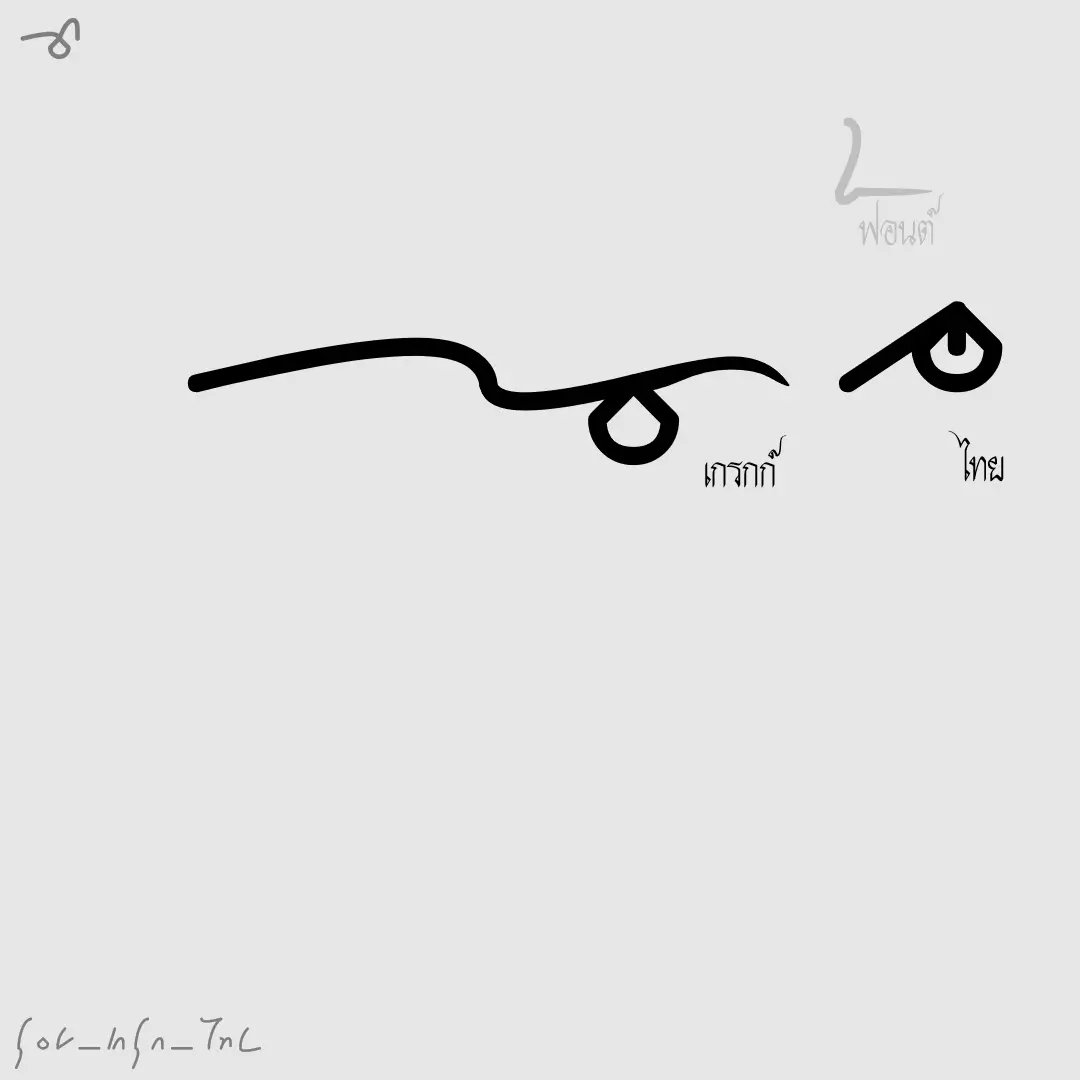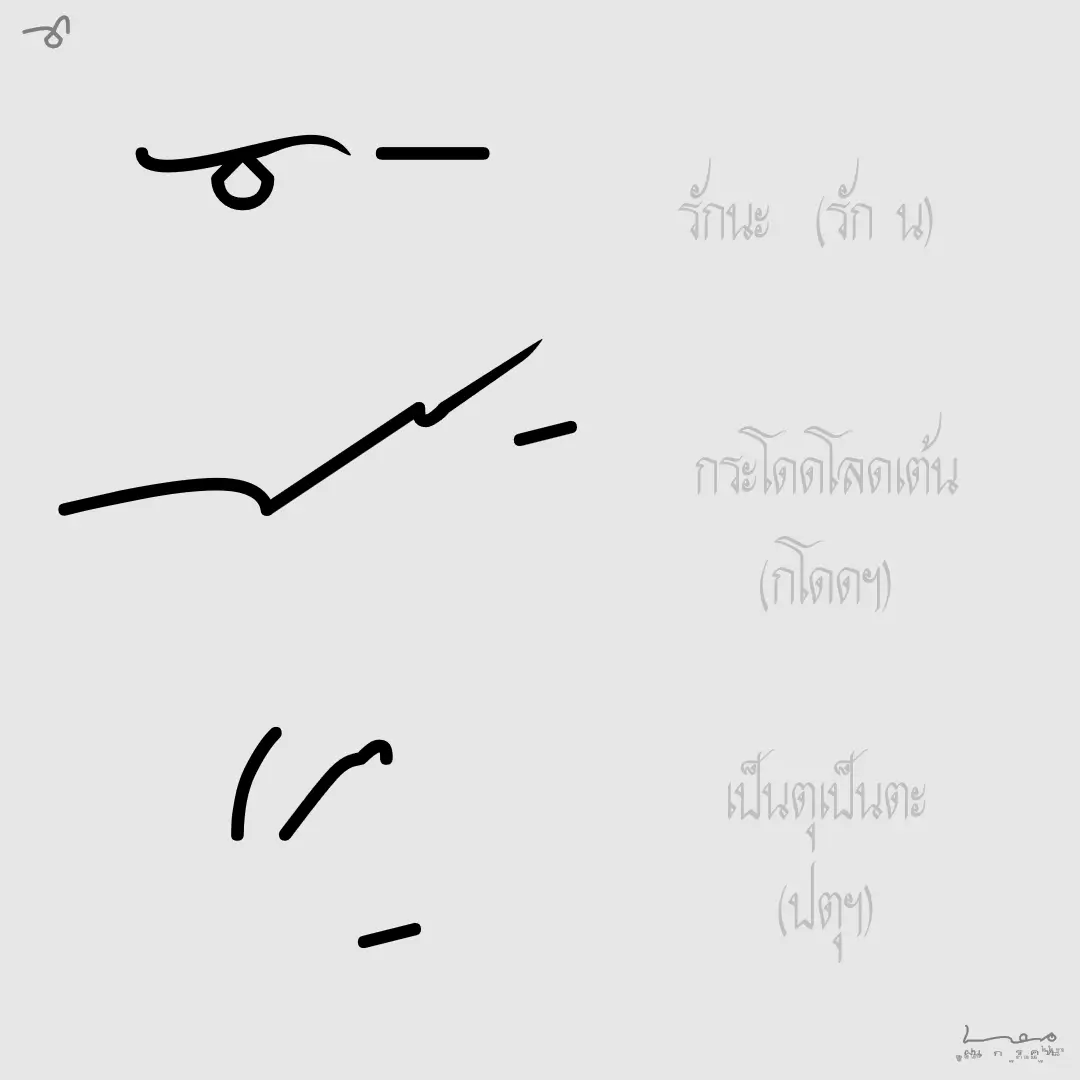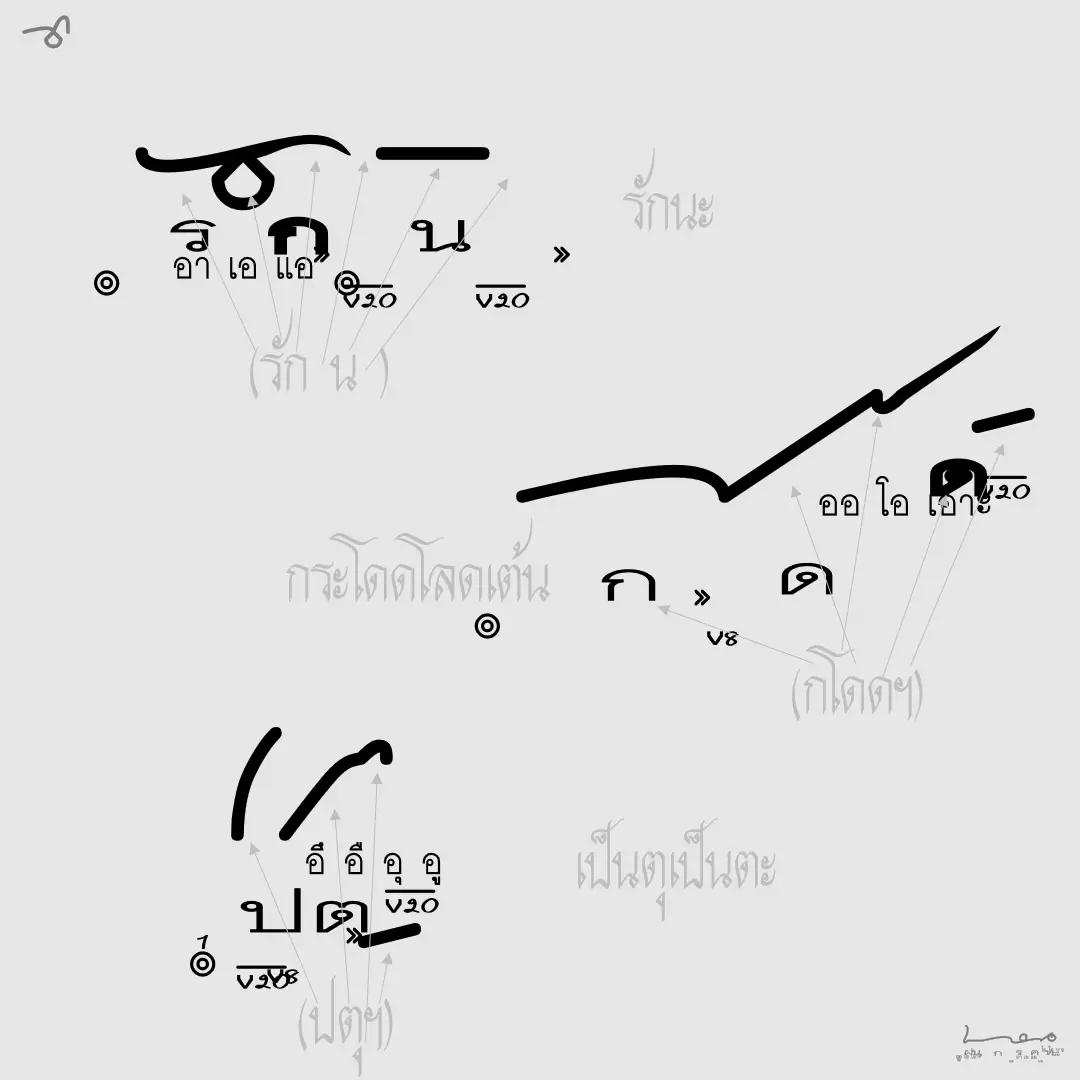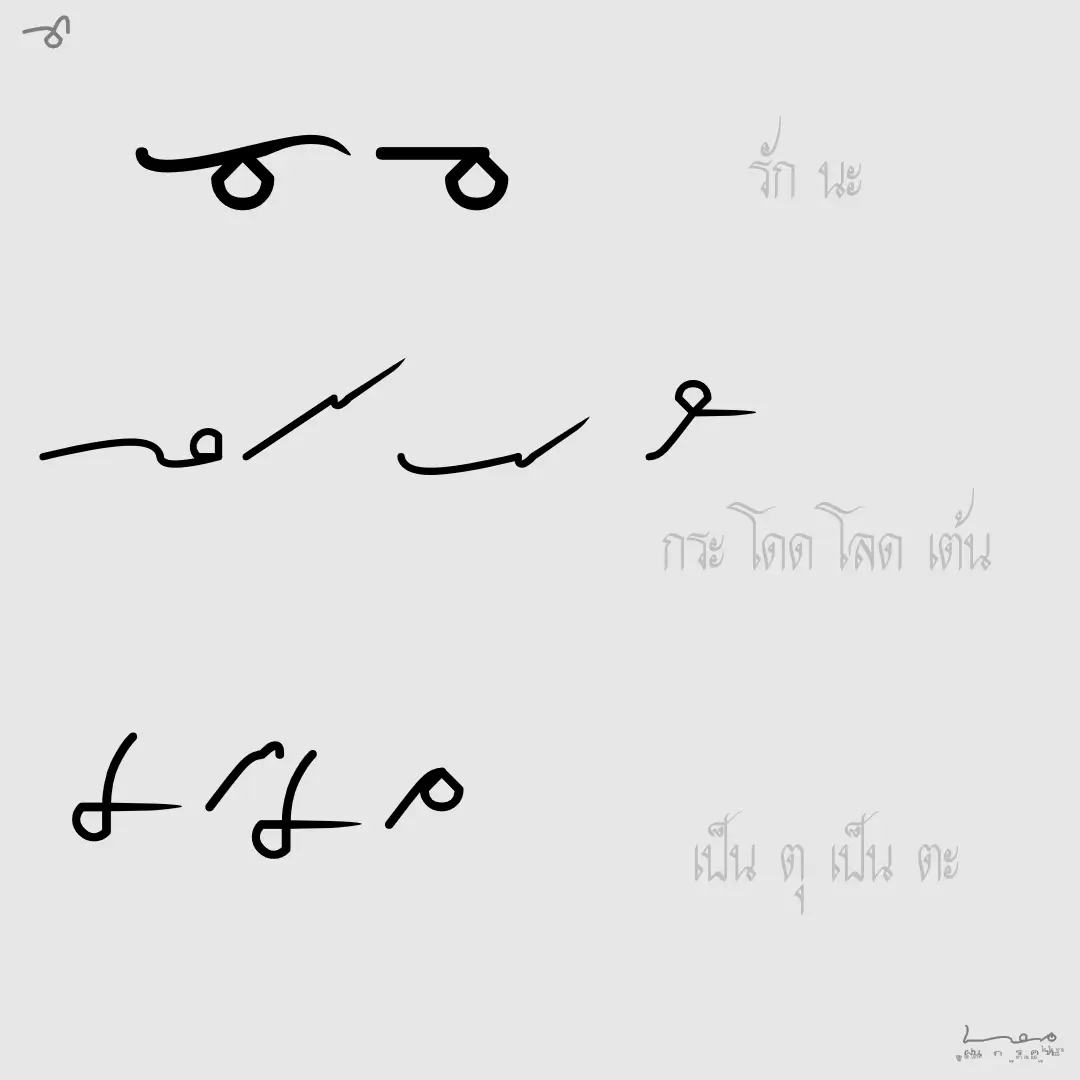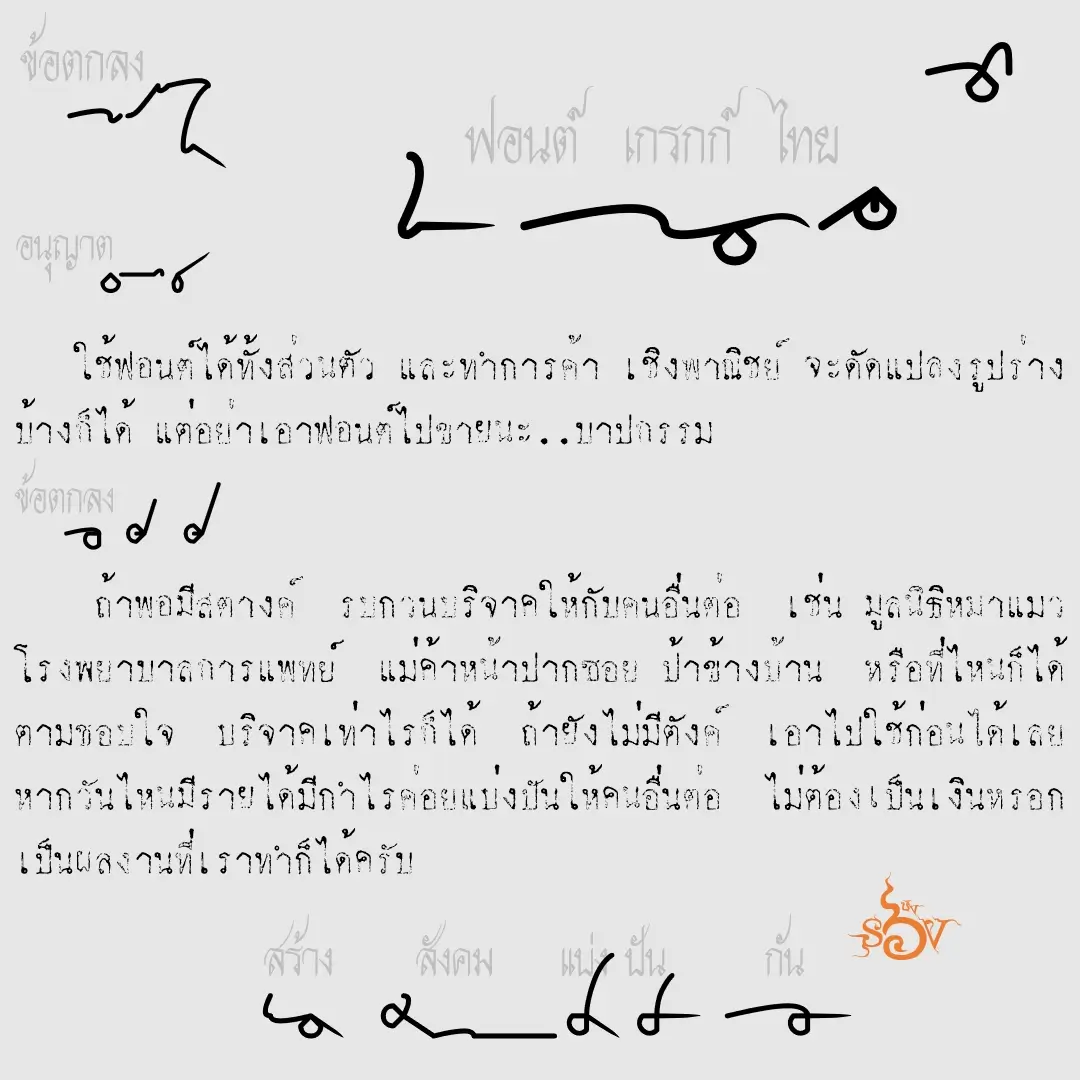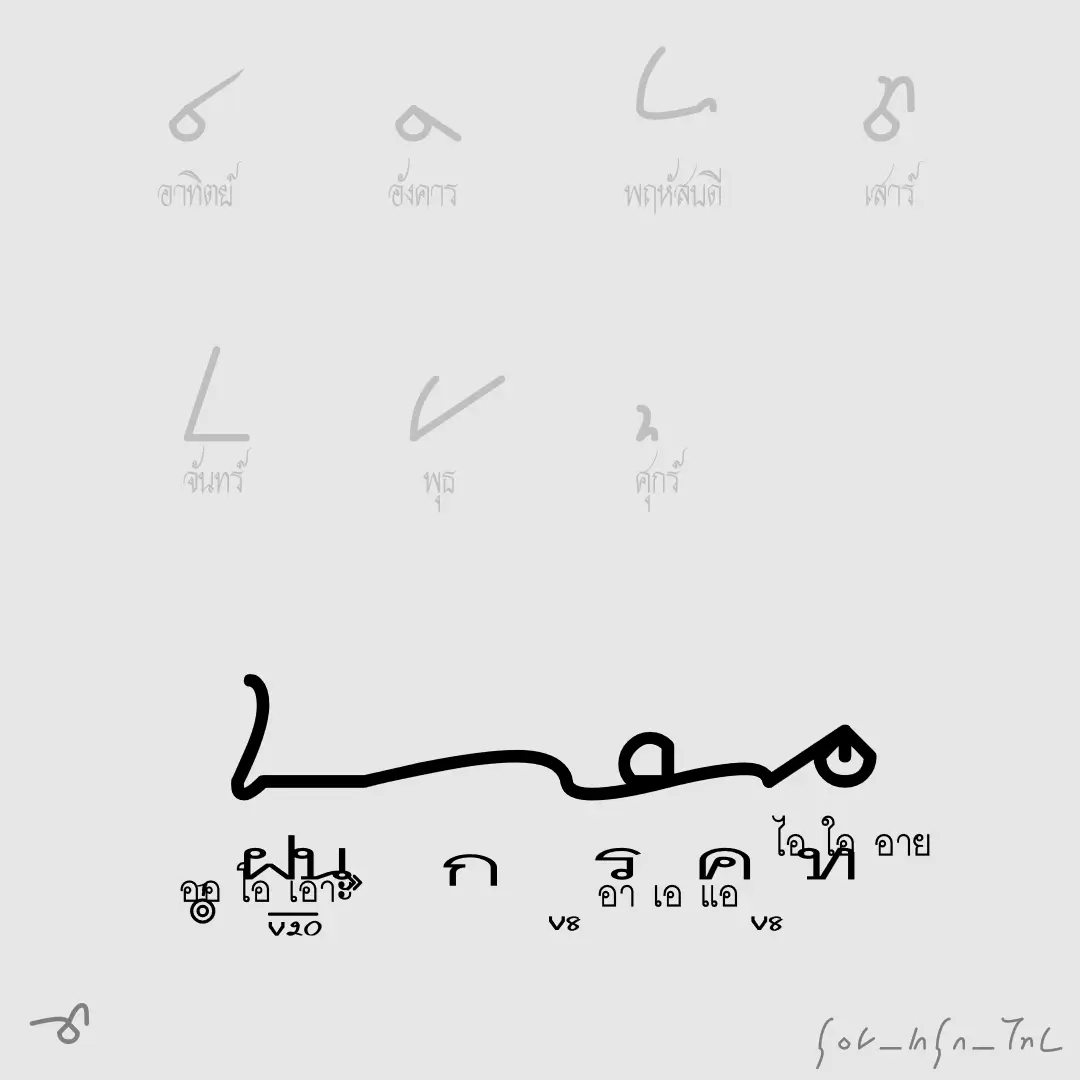
ฟอนต์เกรกก์ไทย – เป็นฟอนต์ทดลอง อักษรชวเลขแบบเกรกก์ ทำเสร็จไป 80% แต่คิดว่าพอก่อน…
ตัวอักษรไม่มีความกว้าง ต้องเคาะ space ให้เลยตัวอักษรที่เห็นเอาเอง และต้องศึกษาชวเลขก่อน ส่วนการอ่านถ้าชวเลขยังไม่คล่องใช้ตัวปรกติ ถ้าคล่องแล้วใช้ตัวหนา (กด bold)
เบื้องหลังการออกแบบ : ฟอนต์ เกรกก์ไทย
เกรกก์ไทย (SOV_greg_tai)